Umělá inteligence postupně proměňuje způsob, jakým vzniká vizuální komunikace značek. Typografie, která byla dlouhou dobu doménou zkušenosti, citu pro detail a manuální práce, se dnes dostává do prostředí, kde ji ovlivňují data, algoritmy a automatizované procesy. Tento posun se neprojevuje pouze ve zrychlení práce, ale také ve změně samotného uvažování o písmu.
Pro značky má typografie zásadní význam. Ovlivňuje čitelnost, důvěryhodnost i celkové vyznění sdělení. Právě proto je důležité porozumět tomu, jak umělá inteligence vstupuje do její tvorby a jaké možnosti i omezení přináší.
Automatizace a její hranice v typografii
S rozvojem AI se nabízí otázka, zda může být typografie do značné míry automatizována. Algoritmy dnes dokážou generovat návrhy písma, upravovat jeho proporce nebo vytvářet varianty pro různé formáty a zařízení.
Přesto zůstává typografie oblastí, kde lidské rozhodování nelze plně nahradit. Písmo totiž nenese pouze vizuální podobu, ale také význam, kulturní souvislosti a emocionální náboj. I drobná změna v tvaru nebo rytmu písma může zásadně ovlivnit to, jak je sdělení vnímáno.
Umělá inteligence proto funguje především jako nástroj, který rozšiřuje možnosti práce. Pomáhá zpracovat velké množství variant a urychluje orientaci v nich, ale finální volba stále vyžaduje citlivé posouzení a pochopení identity značky.
Jak Monotype využívá umělou inteligenci při práci s typografií
Zajímavý posun v této oblasti představuje přístup společnosti Monotype, která dlouhodobě spravuje rozsáhlé knihovny fontů a podílí se na vývoji typografických nástrojů. Právě zde vznikají řešení, která ukazují, jak lze umělou inteligenci využít prakticky a zároveň smysluplně.
Jedním z příkladů je nový způsob vyhledávání písem založený na AI, který reaguje na dlouhodobou zkušenost designérů s tím, že samotné hledání vhodného fontu může být zdlouhavé a odvádět pozornost od návrhu. Tradiční filtrování podle kategorií často neodpovídá tomu, jak designéři přemýšlejí o vizuálním stylu.
Nový přístup proto umožňuje popsat požadovaný charakter typografie přirozeným jazykem – například pomocí výrazů, které vystihují atmosféru nebo osobnost značky. Systém následně pracuje s významem těchto zadání a nabízí odpovídající návrhy. Výběr písma se tak posouvá od technického procesu směrem k intuitivnějšímu rozhodování.
Tento způsob práce zároveň pomáhá udržet pozornost v kreativní rovině. Místo procházení rozsáhlých databází se designér může soustředit na to, jak typografie komunikuje a jak zapadá do celkového vyznění značky. Umělá inteligence zde funguje jako podpora, která zjednodušuje orientaci a urychluje práci, aniž by nahrazovala samotné rozhodování.
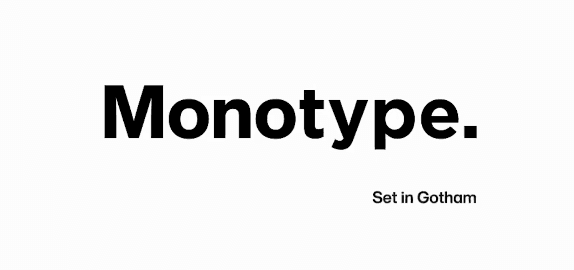
Personalizace a variabilní typografie
Jedním z výrazných posunů, které umělá inteligence přináší, je možnost personalizace typografie. Písmo už nemusí být pevně dané, ale může se přizpůsobovat konkrétním situacím, médiím nebo uživatelům.
Typografie tak může reagovat například na velikost obrazovky, způsob použití nebo kontext sdělení. V praxi to znamená, že značka může zachovat jednotný vizuální styl, ale zároveň jej flexibilně upravovat podle aktuálních potřeb.
Tento přístup posouvá branding směrem k dynamičtějším systémům, které nejsou založeny na jedné neměnné podobě, ale na promyšlené variabilitě.
Typografie jako součást širšího systému práce se značkou
V digitálním prostředí typografie neexistuje izolovaně. Je součástí širšího systému, ve kterém se pracuje s obsahem, vizuální identitou a konzistencí napříč kanály.
V praxi se proto stále častěji využívají nástroje, které umožňují typografii spravovat systematicky. BrandCloud zde může sloužit jako příklad řešení, které pomáhá organizovat vizuální obsah, udržovat jednotný styl a zajistit, že typografie odpovídá nastavené identitě značky napříč výstupy.
Takový přístup umožňuje efektivně pracovat s typografií ve větším měřítku a zároveň udržet konzistentní vizuální identitu značky.
Směr, kterým se typografie v digitálním prostředí ubírá
Vývoj umělé inteligence naznačuje, že práce s typografií bude stále více propojena s daty, automatizací a adaptivními systémy. Designéři budou mít k dispozici nástroje, které jim umožní rychleji testovat varianty, lépe pracovat s kontextem a efektivněji spravovat rozsáhlý obsah.
Současně však zůstává důležité zachovat lidský přístup k tvorbě. Typografie není pouze technická disciplína, ale také prostředek, kterým značka komunikuje svou identitu a hodnoty.
V praxi se proto prosazuje kombinace obou přístupů. Umělá inteligence přináší nové možnosti a zjednodušuje procesy, zatímco designér zajišťuje smysluplnost, originalitu a citlivé uchopení detailu. Právě v tomto propojení vzniká prostor pro kvalitní a dlouhodobě udržitelný branding.